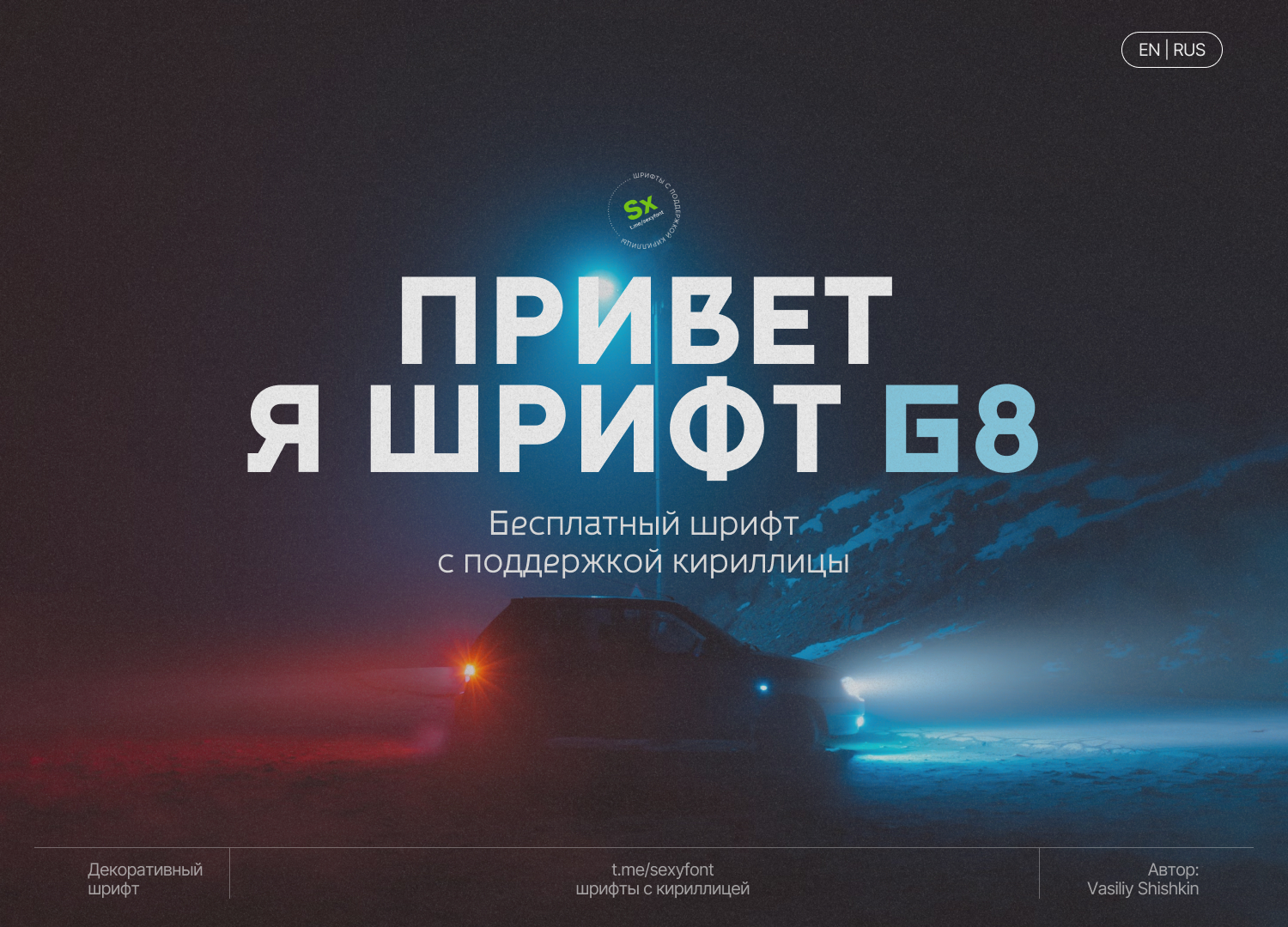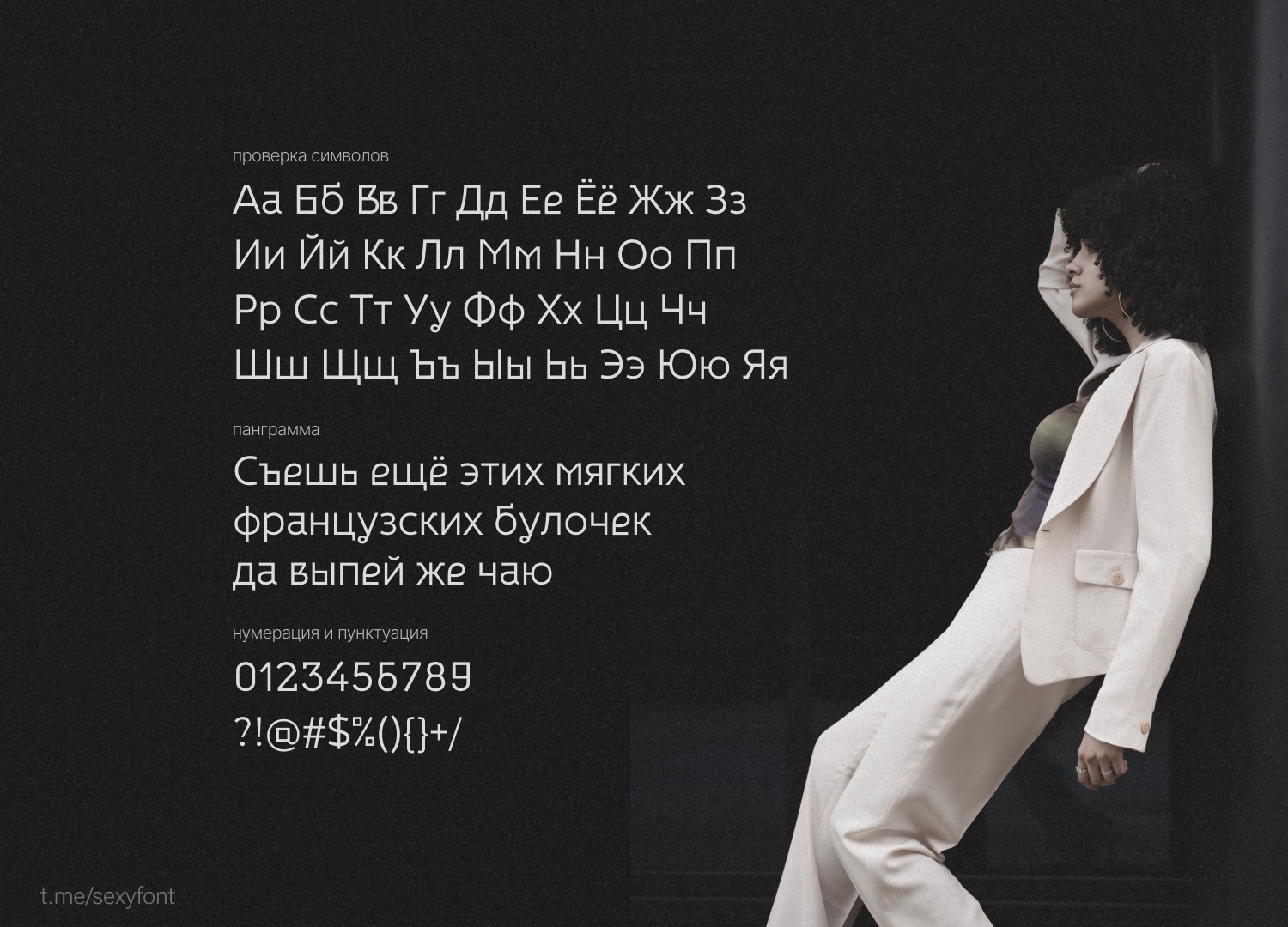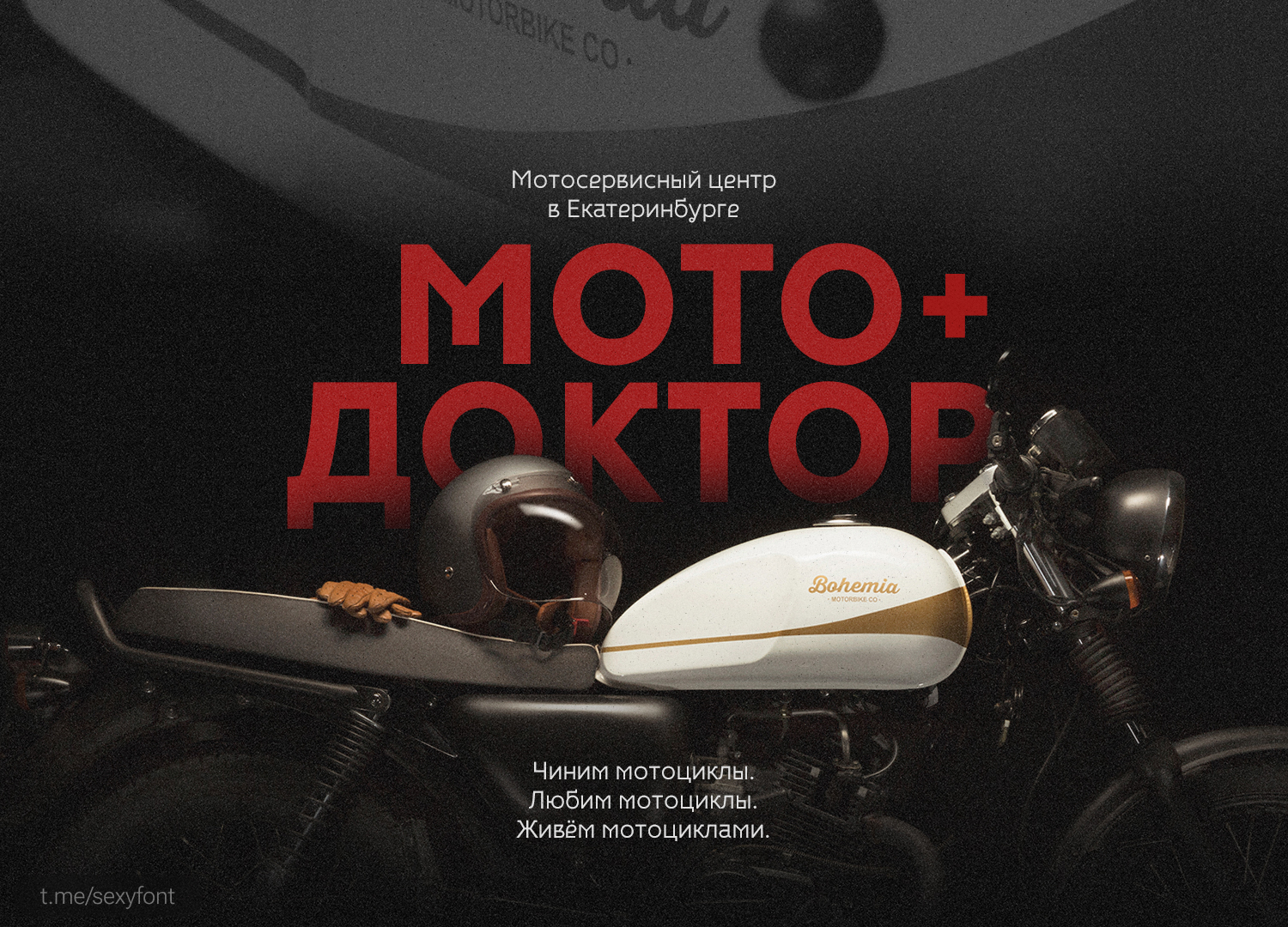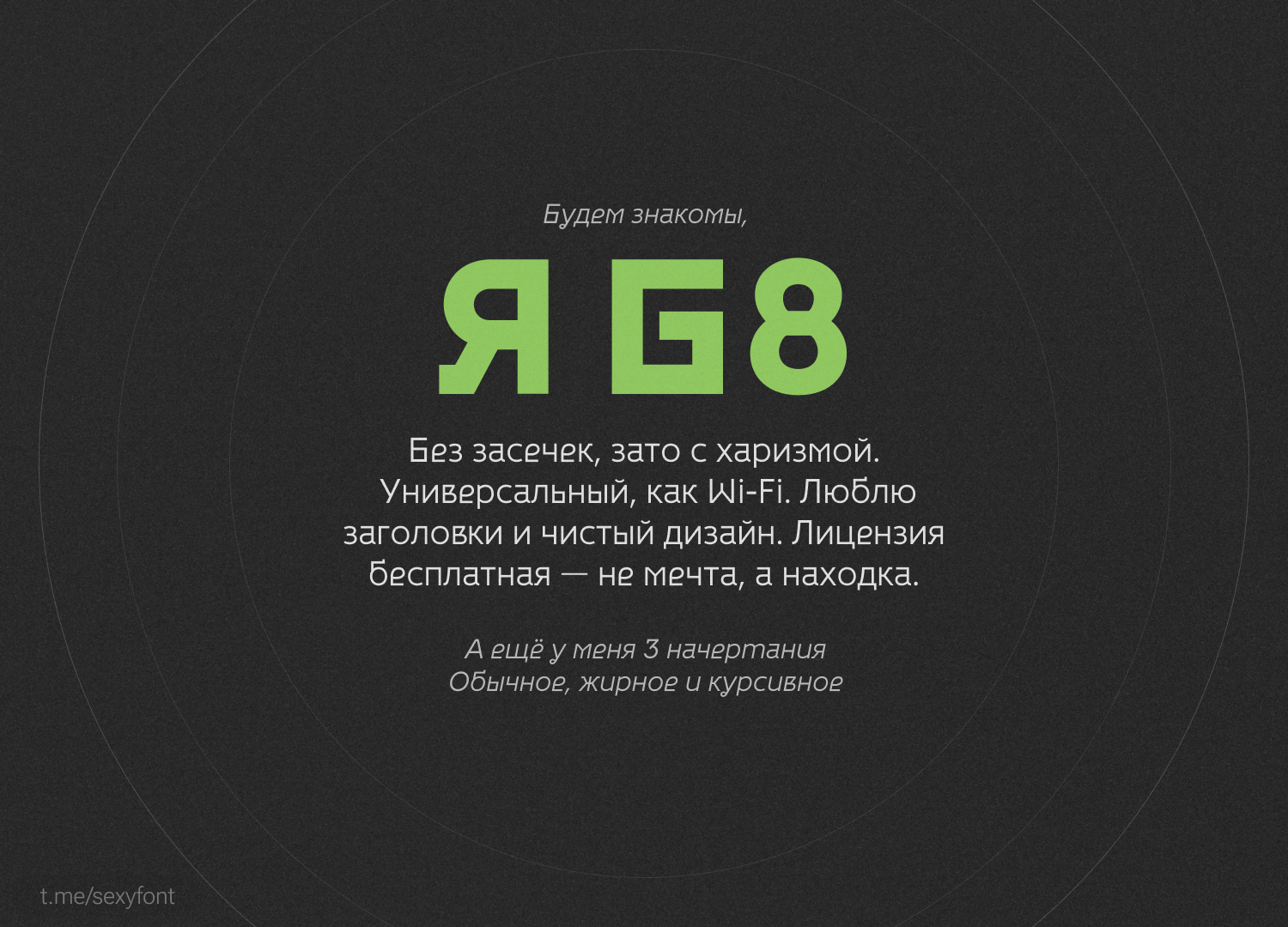
Шрифт G8
Привет, я G8.
Я — минималист, но не скучный.
Меня легко читать, трудно забыть.
Люблю заголовки, логотипы и чистый дизайн.
Говорю на 29 языках и подхожу для любого проекта.